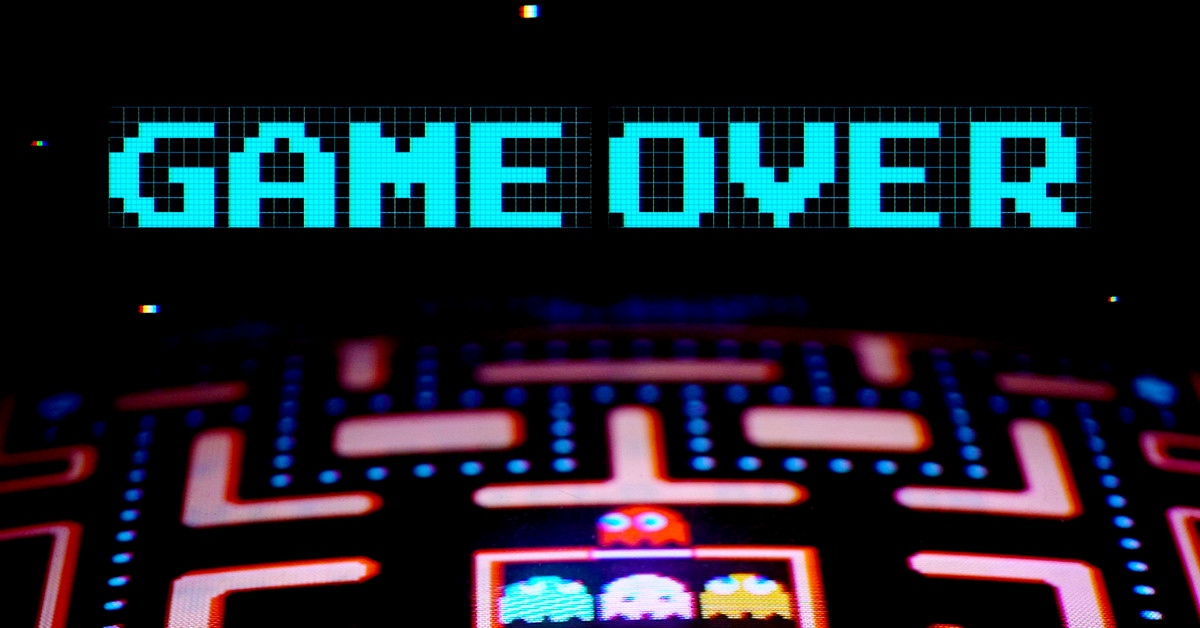
Лучшие 8-битные шрифты (БЕСПЛАТНО / Премиум) 2022
Совершите путешествие в прошлое с нашей потрясающей подборкой 8-битных шрифтов и сделайте нотку ностальгии неотъемлемым аспектом вашей типографики.
Примененные к любому тексту, эти шрифты способны вернуть воспоминания о том, как Супер Марио исследовал Грибное королевство, пытаясь спасти принцессу, другими словами, о 80-х годах.
Пиксельные элементы вместе с необработанными краями превращают надписи в причудливую графику с элементами видеоигр. Используйте любой из них в своих веб-сайтах или игровой графике, футболках или любых других проектах как таковых, и следующее, что вы знаете, вы и ваша аудитория вспоминаете о старых добрых временах.
Лучшие 8-битные шрифты
Ниже представлены некоторые из захватывающих 8-битных шрифтов, которые мы предлагаем как в бесплатных, так и в премиальных категориях, и они производят более захватывающее впечатление. Мы также рекомендуем ознакомиться с нашей подборкой лучших аркадных шрифтов, чтобы составить наилучшую комбинацию.
Ретро детский векторный алфавит
Векторный шрифт Retro kiddo показывает дизайн восьмидесятых и 8-бит. Мы можем использовать этот шрифт для видеоигр, которые интересны детям, для головоломок и даже ретро-игр. Кроме того, вы можете использовать его для дизайна футболок.
Minecraft
Шрифт Minecraft вдохновлен одноименной игрой. Вы можете видеть этот 8-битный шрифт, который в некоторых буквах имеет пикселизацию, а в некоторых не соответствует этому правилу, поэтому вы можете использовать другой дизайн для дизайна своих видеоигр и создавать другое и интересное меню.
Level Up
Шрифт Level Up выполнен в цифровом и квадратном виде.
Этот шрифт очень интересен и практичен в больших размерах, и вы можете использовать его для оформления рекламных щитов и досок казино.
Fipps
Шрифт Fipps является одним из наиболее широко используемых дизайнов, и если вы играли в видеоигры в детстве, вы, должно быть, видели этот 8-битный шрифт, и вы можете использовать его для оформления всех видеоигры, пиксельные анимации, футболки и всевозможные бренды игрушек.
Game Over 8Bit
Game Over 8Bit Шрифт выполнен в стиле ар-деко и ретро. Вы можете использовать этот шрифт для оформления логотипа, меню и названий видео различных игр с различной тематикой, включая головоломки, приключения.
Rixel — это экранный шрифт, вдохновленный пиксельными и 8-битными шрифтами, используемыми в компьютерных играх старой школы. Его закругленные края создают сильный и современный вид, который можно использовать в различных проектах, от редакционного дизайна до анимационной графики! Он был создан для развлечения, и пока вы получаете удовольствие от его использования, вы делаете это правильно! Содержит прописные и строчные буквы, цифры и наиболее популярные символы.